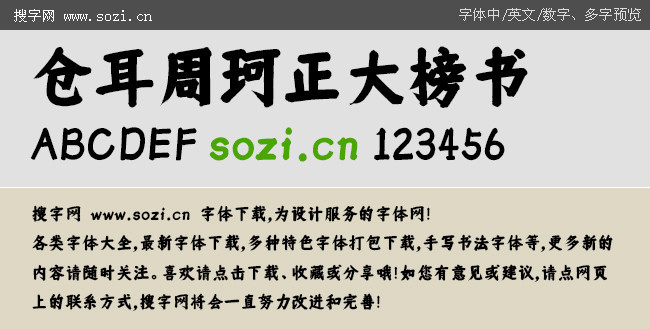
倉(cāng)耳周珂正大榜書
搜字網(wǎng)提供一款倉(cāng)耳周珂正大榜書中文藝術(shù)字體下載,倉(cāng)耳周珂正大榜書是由倉(cāng)耳字庫推出的一款免費(fèi)字體,共收容漢字6763個(gè),英文及標(biāo)點(diǎn)等常用字符245個(gè)。該字體筆觸粗細(xì)適中,字形端正,具有很好的視覺感。